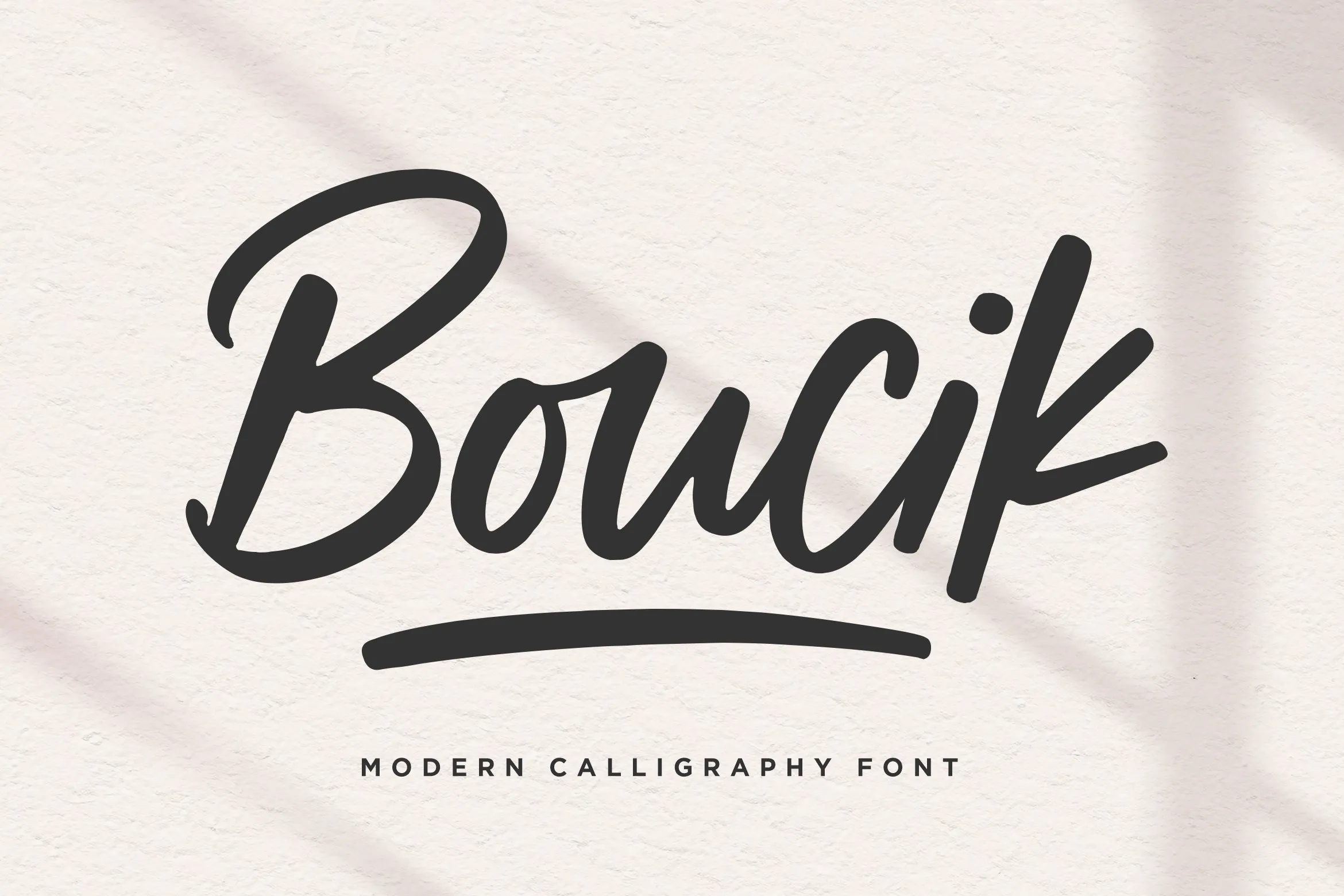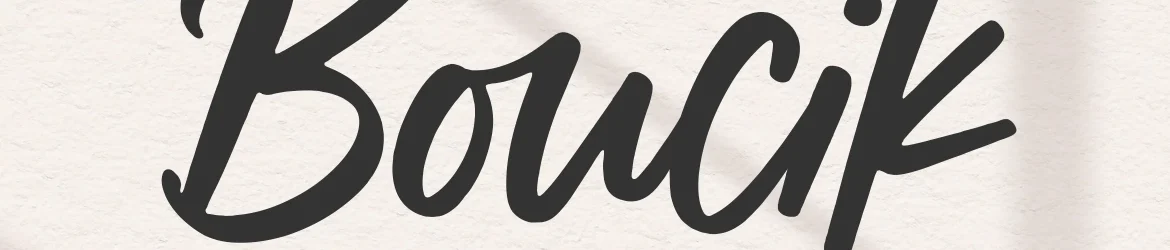
Boucik é uma fonte tipográfica script que oferece um equilíbrio perfeito entre modernidade e elegância. Seu design relaxado e adaptável torna-o a escolha ideal para criar logos impressionantes, marcas de marca criativas ou frases impactantes. Cada letra possui sua personalidade única e beleza natural, garantindo que seu trabalho se torne algo realmente especial. Esta fonte é perfeita tanto para aqueles que desejam incorporar um touch artístico em projetos gráficos quanto para quem busca uma solução rápida para expressar seus pensamentos de maneira elegante. Balpirick é o autor da Boucik, uma fonte que certamente vai adicionar um toque único e vibrante aos seus designs.